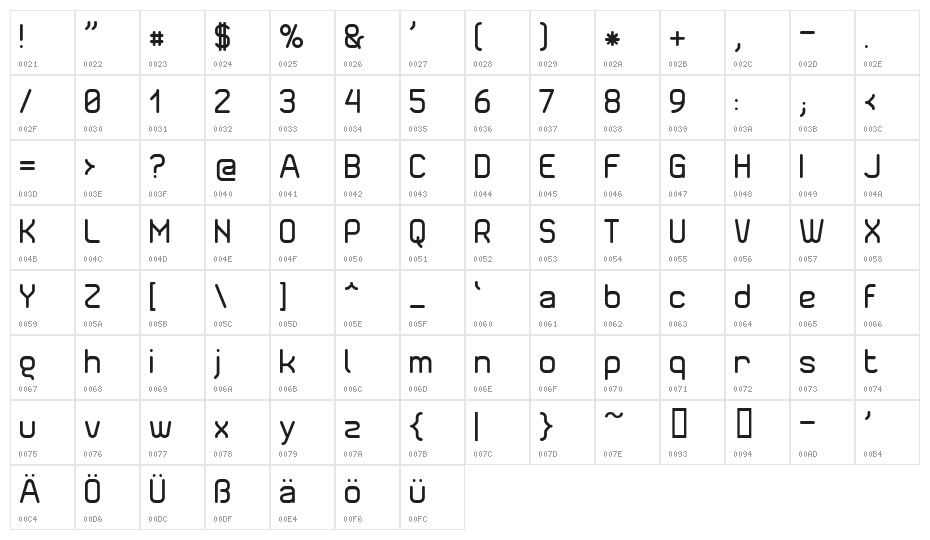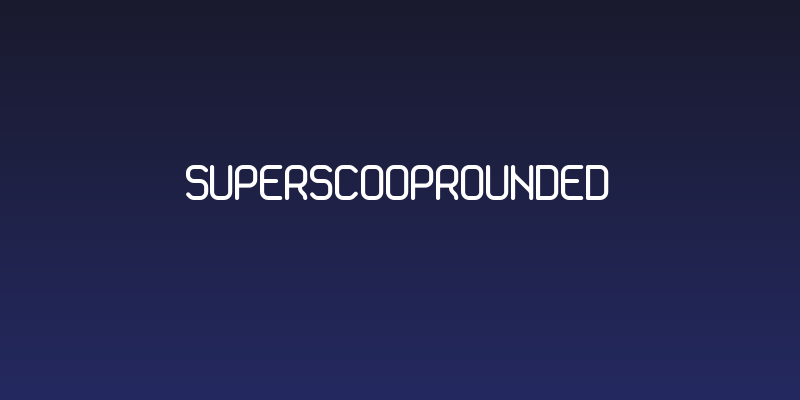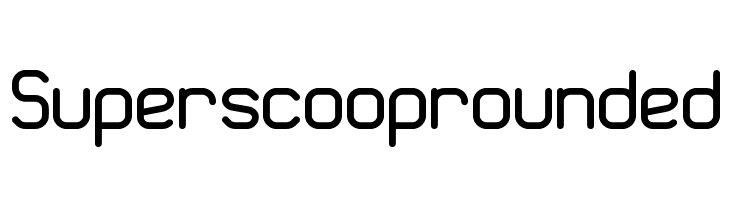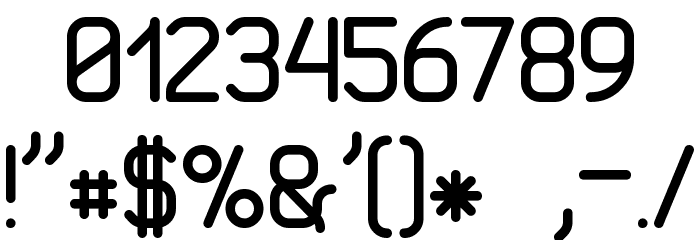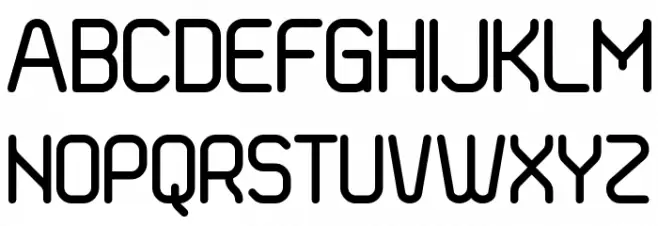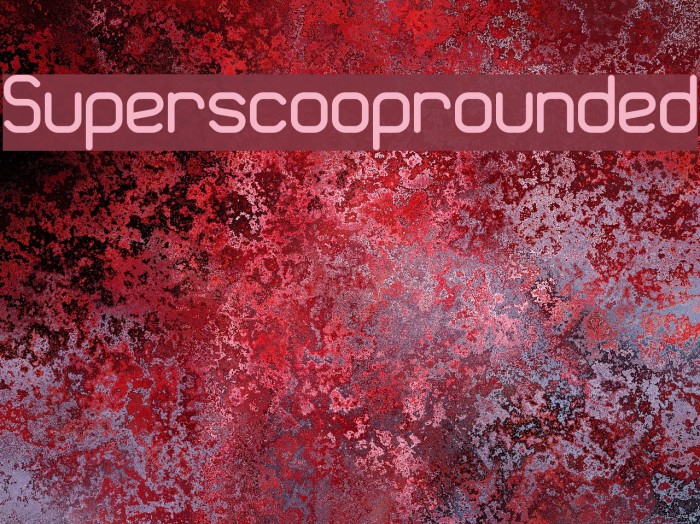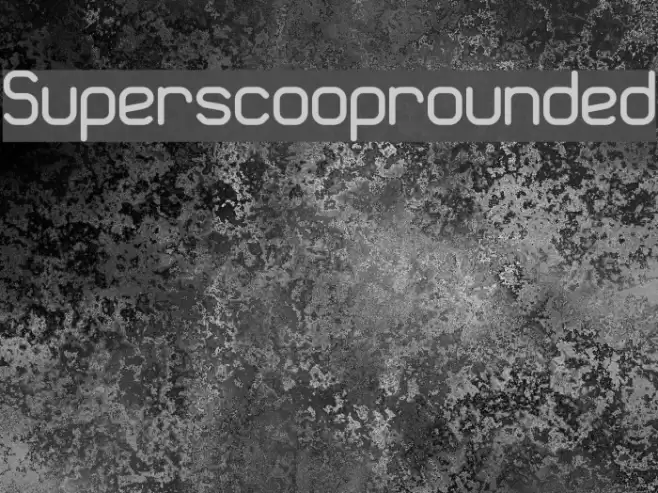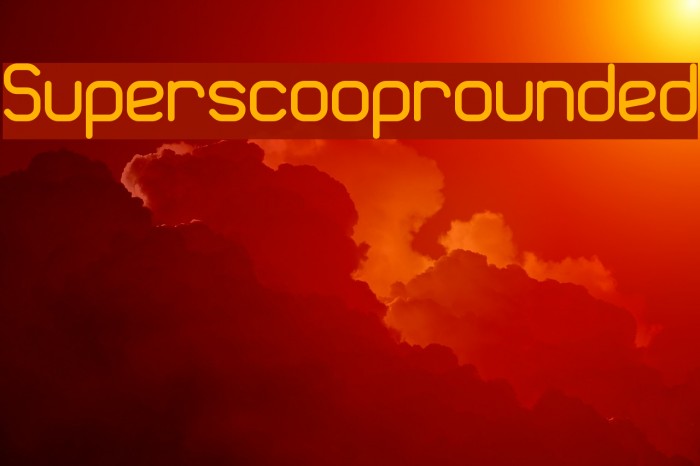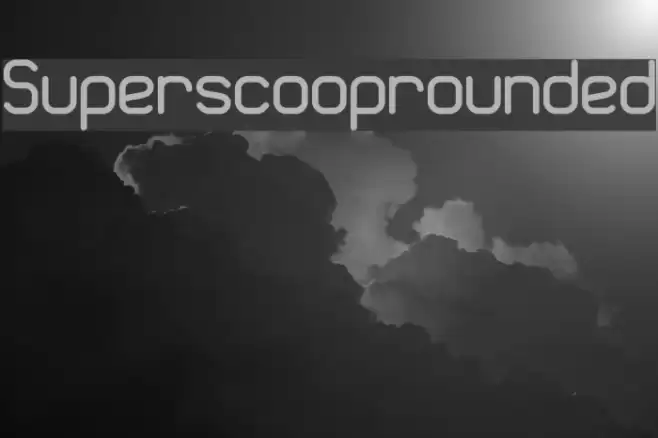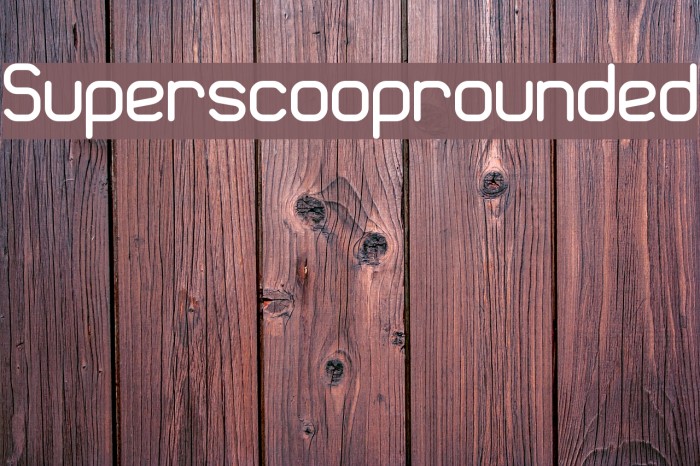
Superscooprounded Font
| Caz de utilizare | Headlines, Logos, Digital interfaces |
| Proiecte propuse | Ideal for branding, packaging, digital interfaces, and children's products due to its friendly and approachable style. |